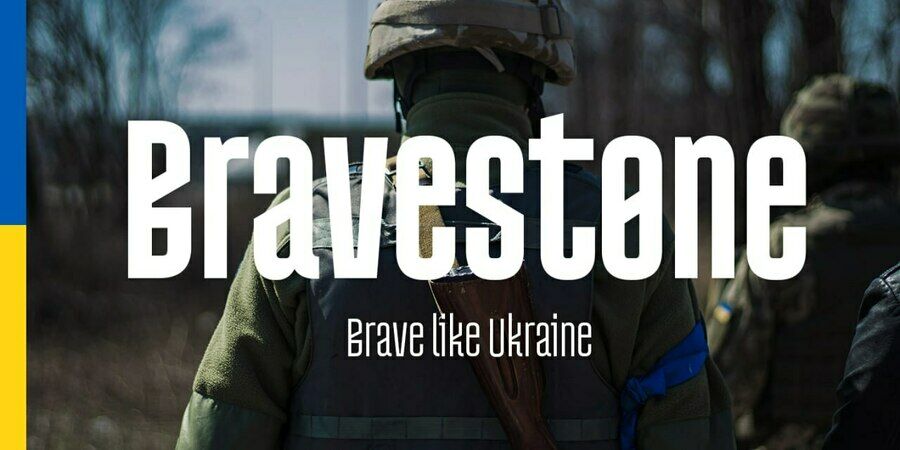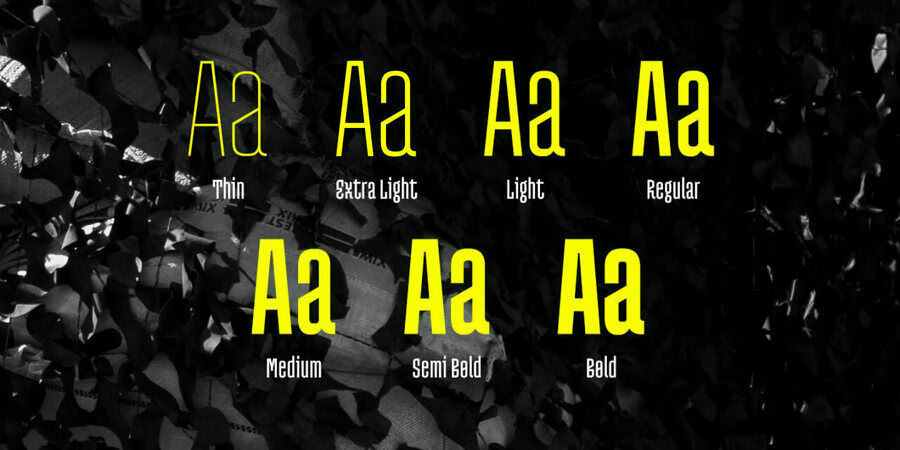
Bravestone – вузький акцидентний гротеск, який в собі поєднує як експериментальні форми так і відсилки до кирилічної в'язі. Завдяки оригінальним рішенням шрифт має сміливий і яскравий характер. Bravestone розроблено для логотипів, назв, обкладинок книг і фірмової ідентичності. Ви також можете використовувати його для невеликих фрагментів тексту. Шрифт розробили Кирило Ткачов та Сергій Макаренко у 2024 році.
Асоціації з сімейством шрифтів BravestoneОсобистість і характер гарнітури:
тонкий, стрункий, худий, рівний, статичний, високий, міський, вузький, технічний, якісний, точний, чіткий, крихкий, прозорий, дротяний, прямокутний, гострий, ламаний, холодний, скляний, сучасний, інженерний, креслярський, прямий, неоновий, іронічний, дивний, характерний, оригінальний, самобутній, серйозний, стиснений, стійкий, твердий, гучний, впевнений, тісний, помітний, грайливий, яскравий, архітектурний, загадковий, окультний, містичний, екзотичний, рубаний, амбітний, важливий, мотивуючий, переконливий, міцний, різкий, експериментальний, грубий, сміливий, урбаністичний, виразний, андеграундний, гаражний, ритмічний, сильний, брутальний, техногенний, індустріальний, мужній, значний, надійний, суворий, активний, крутий, робочий, екстремальний, ризикований, вуличний, жорсткий, революційний, небезпечний, зухвалий, радикальний, потужний, важкий, кричущий, нічний, залізний, сталевий, чорний, авторитетний, наполегливий, екстравагантний
Місто, дієта, архітектура, електроніка, кафе, хмарочос, пряник, сувенір, скульптура, пам'ятник, монета, квест, туризм, завод, промисловість, будівництво, гра, комп'ютерна гра, нічний клуб, техніка, інструмент, будматеріали, верстат, індустрія, енергетика, джинси, ремонт, блокбастер, робочий, каскадер, екстрим, гараж, фестиваль, рок, страйк, Протест, реп, хіп-хоп, концерт, рок-н-рол, шолом, інсектицид, пестицид, бомба, металургія, екскаватор, зброя, сталевар Гарнітура має ознаки стилів: